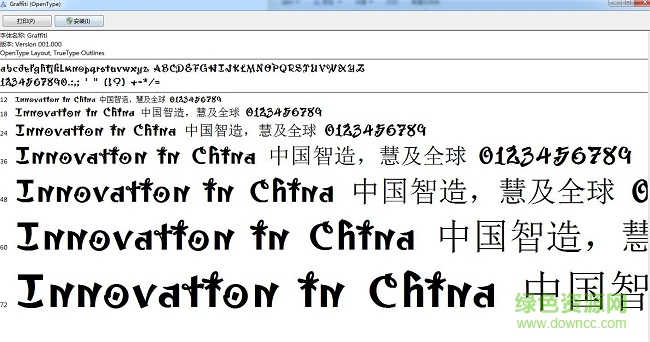
migraffiti字體是一款非?;ㄇ蔚?a href="http://573ee.cn/k/gexingziti/" target="_blank">個(gè)性字體,線條裝飾多,變化自然,整體感覺華麗好看,綠色資源網(wǎng)還有超多創(chuàng)意字體可供下載,喜歡的朋友快來體驗(yàn)吧!
裝飾字體是在基本字形的基礎(chǔ)進(jìn)行裝飾、變化加工而成的。它的特征是在一定程度上擺脫了印刷字體的字形和筆劃的約束,根據(jù)品牌或企業(yè)經(jīng)營性質(zhì)的需要進(jìn)行設(shè)計(jì),達(dá)到加強(qiáng)文字的精神含義和富于感染力的目的。
字體的藝術(shù)性體現(xiàn)在其完美的外在形式與豐富的內(nèi)涵之中。 字體是文化的載體,是社會(huì)的縮影。